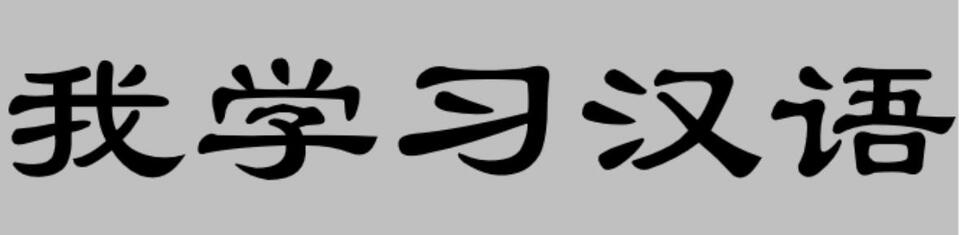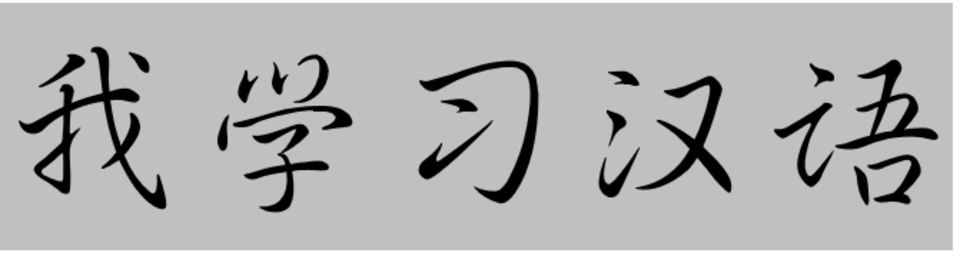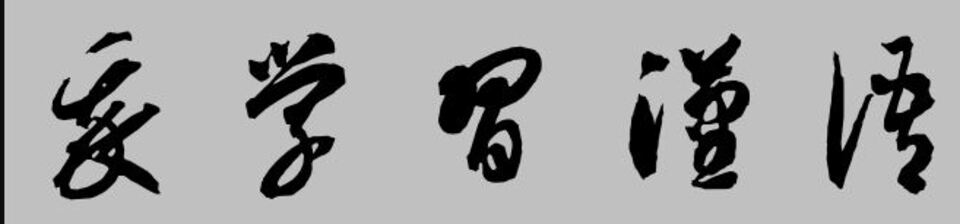
Hàng trăm font tiếng Trung: Lựa chọn hoàn hảo cho mọi thiết kế mà bạn nên khám phá
Tìm hiểu font tiếng Trung là gì? Lý do font chữ tiếng Trung được sử dụng rộng rãi ở nhiều quốc gia. Tổng hợp những font tiếng Trung đẹp mắt, thiết kế ấn tượng phù hợp với từng mục đích khác nhau. Hướng dẫn chi tiết cách tải font tiếng Trung trên máy tính bạn có thể tham khảo.
Tiếng Trung ngày càng được sử dụng rộng rãi trên thế giới. Nếu tiếng Việt sử dụng các chữ cái Latinh thì tiếng Trung lại sử dụng chữ cái riêng của mình. Với hàng ngàn ký tự khác biệt, các font tiếng Trung không chỉ cần chính xác mà còn phải linh hoạt và dễ nhìn. Bài viết dưới đây, FPT Shop sẽ tổng hợp những font tiếng Trung đẹp, ấn tượng nhất và hướng dẫn bạn cách cài đặt bộ gõ tiếng Trung một cách dễ dàng trên máy tính.
Font tiếng Trung là gì?
Font tiếng Trung là các bộ ký tự được thiết kế để hiển thị văn bản tiếng Trung Quốc, bao gồm cả chữ Hán giản thể và chữ Hán phồn thể. Khác với các ngôn ngữ sử dụng bảng chữ cái, tiếng Trung có hàng ngàn ký tự riêng lẻ, mỗi ký tự mang ý nghĩa và cách đọc khác nhau. Do đó, các font tiếng Trung cần phải đáp ứng được cả về hình thức và độ chính xác khi hiển thị các ký tự này trên các thiết bị và ứng dụng.
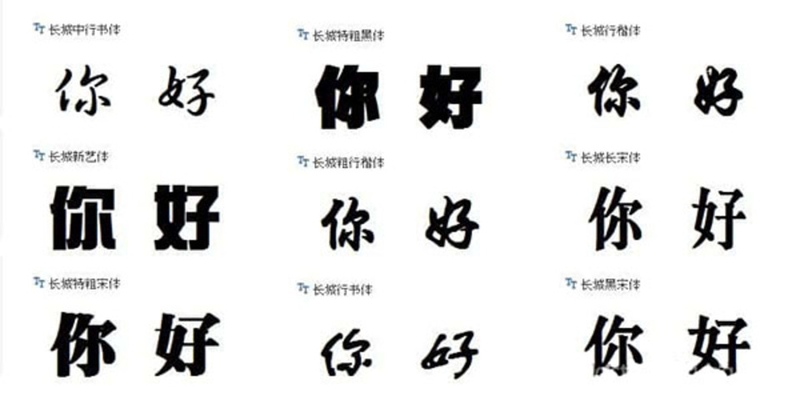
Các font tiếng Trung không chỉ giúp thể hiện ngôn ngữ mà còn mang tính thẩm mỹ cao, ảnh hưởng đến cách truyền đạt và phong cách thiết kế của các tài liệu, trang web, áp phích hay sản phẩm quảng cáo. Mỗi loại font có nét đặc trưng riêng, từ đơn giản, dễ đọc đến phức tạp, nghệ thuật, phù hợp với từng mục đích sử dụng cụ thể.
Các yếu tố quan trọng của font tiếng Trung:
- Khả năng đọc: Khả năng đọc là yếu tố quan trọng nhất của một font tiếng Trung. Font chữ cần phải rõ ràng, dễ đọc và không gây mỏi mắt cho người đọc.
- Độ rộng: Độ rộng của các glyph có ảnh hưởng đến khả năng đọc và bố cục của văn bản. Một số font có glyph rộng hơn và nhiều loại font khác cũng có glyph hẹp hơn.
- Độ dày: Độ dày của nét chữ cũng ảnh hưởng đến khả năng đọc và tính thẩm mỹ của văn bản.
- Khoảng cách giữa các chữ: Khoảng cách giữa các chữ cần phải được điều chỉnh sao cho phù hợp, đảm bảo khả năng đọc và tính thẩm mỹ của văn bản.
- Bộ ký tự: Một font tiếng Trung tốt cần phải có một bộ ký tự đầy đủ, bao gồm các chữ Hán thông dụng, các ký hiệu và các dấu câu.
Tại sao font tiếng Trung được sử dụng rộng rãi?
Font tiếng Trung được sử dụng rộng rãi không chỉ ở Trung Quốc mà còn ở nhiều quốc gia khác, đặc biệt là các cộng đồng người Hoa trên toàn thế giới. Một số lý do khiến font tiếng Trung trở nên phổ biến bao gồm:
- Sự phát triển của tiếng Trung toàn cầu: Với vai trò ngày càng lớn của Trung Quốc trong nền kinh tế và văn hóa quốc tế, nhu cầu sử dụng tiếng Trung cũng tăng cao. Các doanh nghiệp, nhà thiết kế và tổ chức quốc tế cần sử dụng font tiếng Trung để truyền tải thông tin một cách chính xác và chuyên nghiệp.
- Phong cách thiết kế độc đáo: Font tiếng Trung mang tính nghệ thuật và văn hóa riêng biệt. Các nhà thiết kế thường chọn font tiếng Trung để tạo sự khác biệt và ấn tượng cho các sản phẩm sáng tạo như áp phích, logo hay bìa sách.
- Sự đa dạng trong kiểu chữ: Font tiếng Trung không chỉ có một kiểu cố định mà có nhiều phong cách khác nhau, từ đơn giản đến phức tạp. Điều này giúp đáp ứng nhu cầu sử dụng trong nhiều hoàn cảnh, từ văn bản học thuật đến các tác phẩm nghệ thuật.
- Các tiêu chuẩn mã hóa: Sự ra đời và phổ biến của các tiêu chuẩn mã hóa như Unicode đã giúp giải quyết vấn đề hỗ trợ ngôn ngữ tiếng Trung trên các hệ thống máy tính khác nhau, tạo điều kiện thuận lợi cho việc sử dụng rộng rãi font chữ tiếng Trung.
- Yếu tố văn hóa: Việc sử dụng font chữ tiếng Trung là một phần không thể thiếu trong văn hóa của các quốc gia và vùng lãnh thổ sử dụng tiếng Trung. Font chữ không chỉ đơn thuần là công cụ để hiển thị văn bản mà còn là một phần của di sản văn hóa và nghệ thuật.
- Sự cạnh tranh thị trường: Sự cạnh tranh giữa các nhà sản xuất font chữ đã dẫn đến sự phát triển của nhiều font chữ tiếng Trung chất lượng cao với giá cả cạnh tranh, thúc đẩy việc sử dụng rộng rãi hơn nữa.
Tổng hợp các font tiếng Trung đẹp mắt và ấn tượng
Dưới đây là một số font tiếng Trung nổi bật và thường được sử dụng trong nhiều lĩnh vực khác nhau.
Font chữ Simsun
Font Simsun là một trong những font tiếng Trung giản thể phổ biến nhất, thường được cài sẵn trên các hệ điều hành như Windows và macOS. Đây là font chữ dễ đọc, có thiết kế rõ ràng với những nét chữ ngay ngắn, không cách điệu, phù hợp cho các tài liệu, bài viết hay nội dung kỹ thuật số.
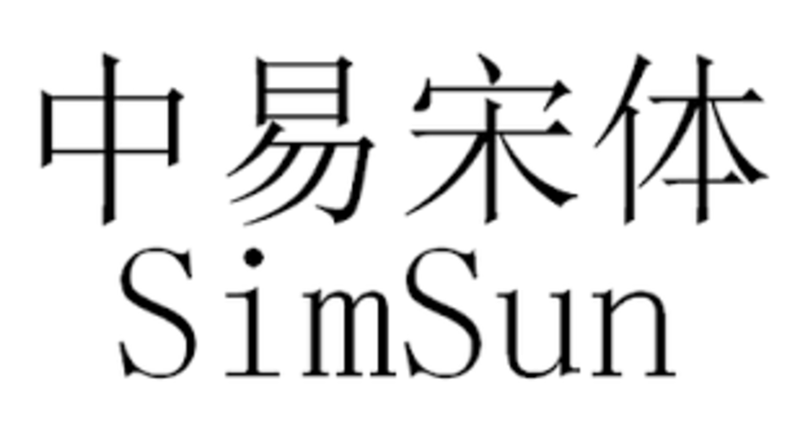
Font chữ DFKAI-SB
DFKAI-SB là một font chữ phồn thể và thường được sử dụng cho các tác phẩm nghệ thuật hoặc tài liệu yêu cầu nét thanh, mảnh. Loại font này có phong cách truyền thống, mang hơi hướng thư pháp nhưng vẫn đủ rõ ràng để sử dụng trong các mục đích hiện đại.
Font chữ Chang Cheng giản thể
Font chữ Chang Cheng là một dạng font chữ giản thể, nó thường được sử dụng trong các thiết kế mang tính biểu tượng và hiện đại. Với các nét chữ thẳng, chắc chắn, loại font này mang đến sự chuyên nghiệp và dễ đọc, phù hợp cho các bài thuyết trình, poster và ấn phẩm truyền thông.